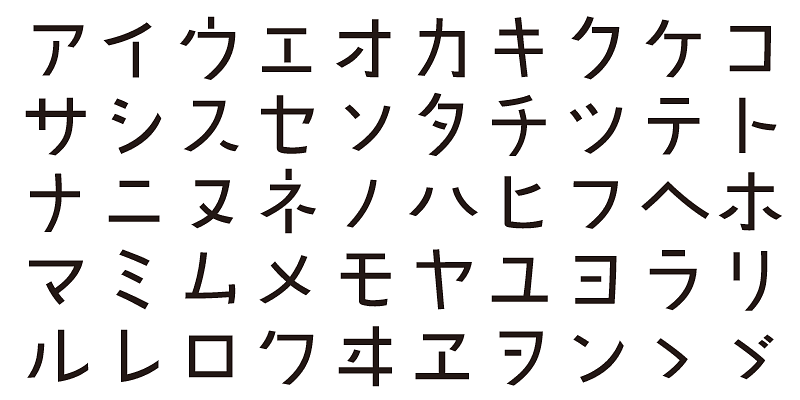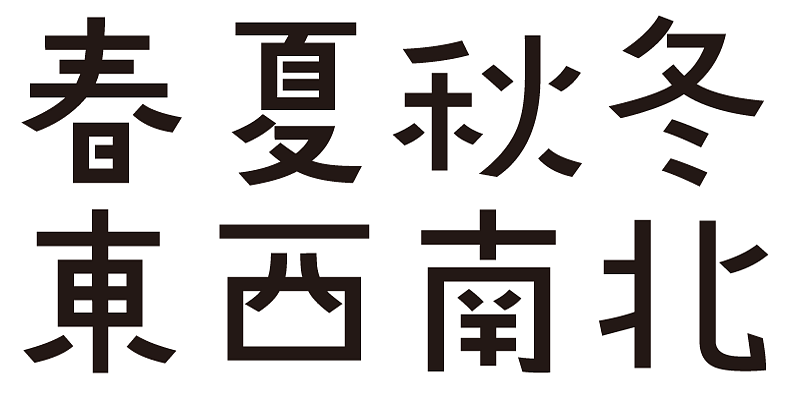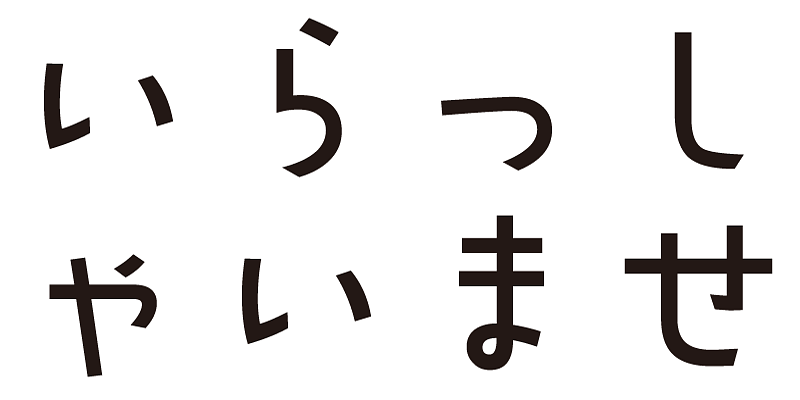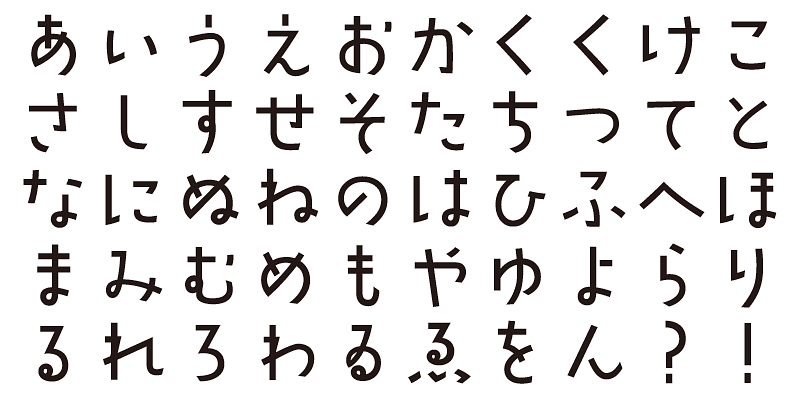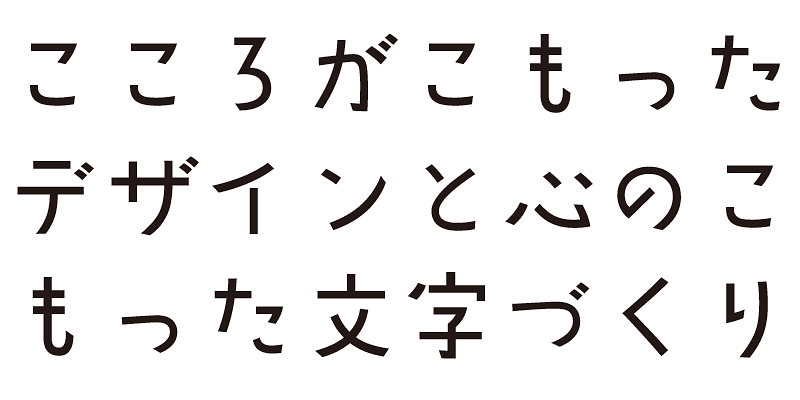
La conception de cette police suit un mouvement au rythme calme et tranquille.
Chaque police de cette famille de polices comprend 1 000 caractères kanji, ainsi que des caractères hiragana, katakana, alphanumériques et des signes de ponctuation.
Nous concevons des polices dans l’espoir qu’elles ajouteront une signification sous-jacente aux mots exprimés. Nous souhaitons que l’utilisateur se sente bien et qu’il éprouve du confort et de la joie lorsqu’il utilise ces polices.